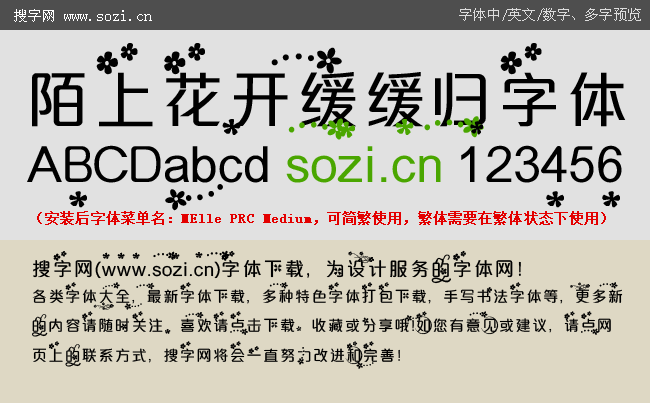
陌上花開(kāi)緩緩歸字體
搜字網(wǎng)給大家提供一款陌上花開(kāi)緩緩歸字體手機(jī)中文字體下載。這款手機(jī)字體是將黑體字體進(jìn)行重新設(shè)計(jì),更加具有藝術(shù)感,字體間又嵌入了了漂亮的花朵圖案。是一款非常藝術(shù)的字體,特別適合喜歡手機(jī)字體個(gè)性一些的朋友在手機(jī)上安裝使用。